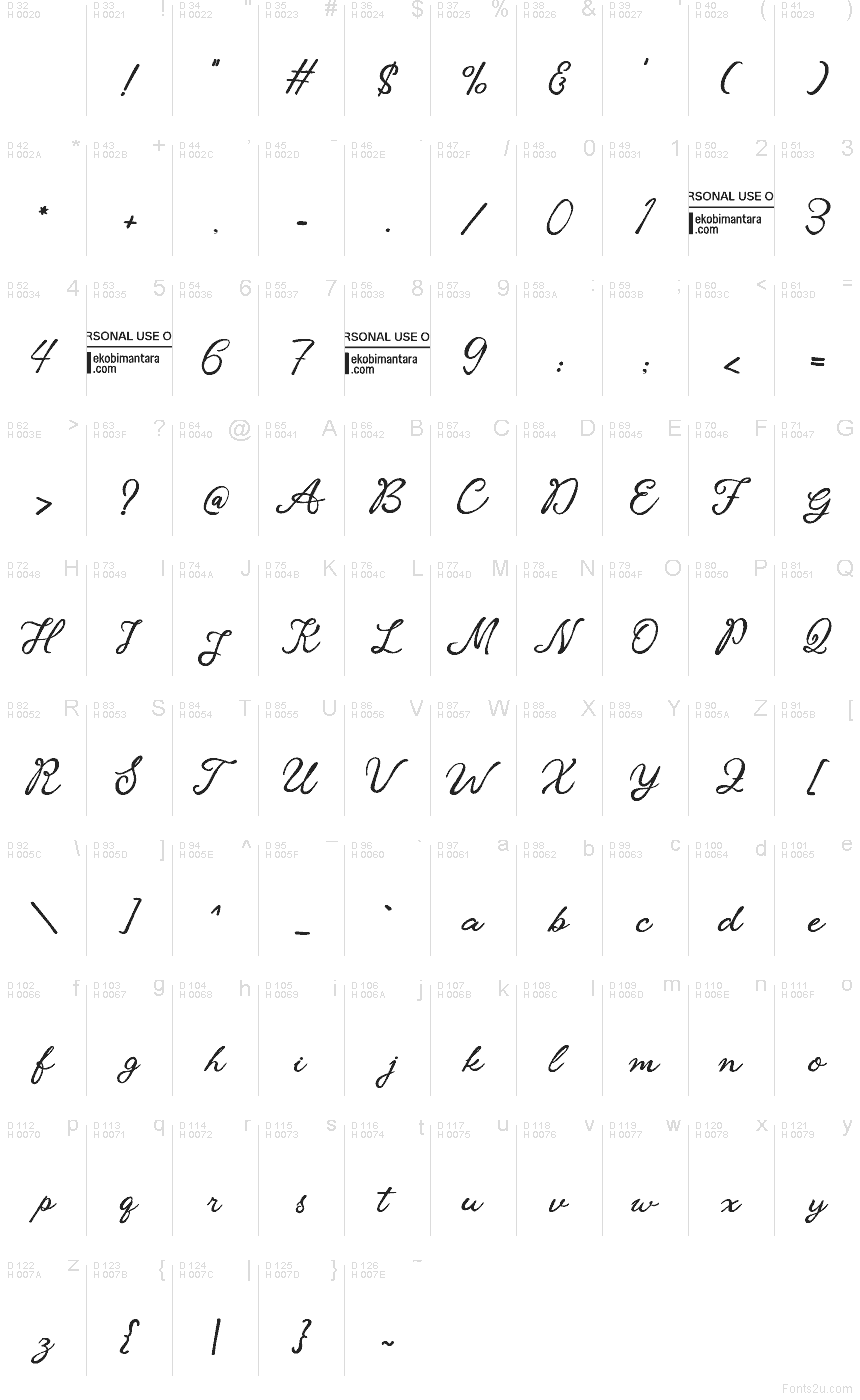
Housemail Script di Eko Bimantara è un carattere calligrafico gratuito caratterizzato da tratti d'attacco ampi ed eleganti, alte anse e marcati passaggi tra fini linee sottili e tratti discendenti corposi. Le sue lettere collegate mantengono ovunque la fluida sicurezza della scrittura formale.
Gli inviti di nozze sono il suo contesto ideale, poiché le ampie decorazioni conferiscono una finitura personale alla cartoleria e si adattano anche al branding di eventi e a monogrammi personalizzati per occasioni formali o romantiche. Nel packaging cosmetico o negli editoriali di moda, le forme ad anello possono richiamare nastri, fili e linee botaniche disegnate a mano, trasformando il lettering in parte dell'immaginario decorativo piuttosto che in una didascalia neutrale.